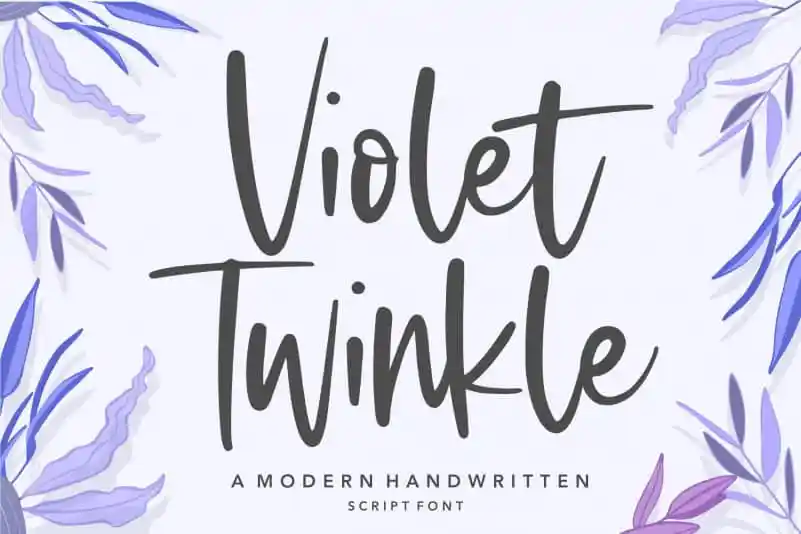
Violet Twinkle Script Font – Download Grátis
A Violet Twinkle Modern Handwritten Script Font é uma delicada escolha para aqueles que buscam um ar moderno em seu design editorial ou design gráfico, ainda assim mantendo a elegância e suavidade de uma fonte escrita à mão. Desenvolvida pelo designer balpirick, esta fonte oferece um toque único de modernidade ao mesmo tempo que preserva a serenidade dos truques manuscritos. A Violet Twinkle é perfeita para criar layouts carregados de emoção e sofisticação, tornando-a uma opção ideal para qualquer projeto que valoriza personalidade e cuidado em suas mensagens visuais. Seja para aplicativos digitais ou design gráfico impresso, esta fonte traz a delicadeza de uma letra escrita à mão sem deixar de manter um visual moderno e contemporâneo.